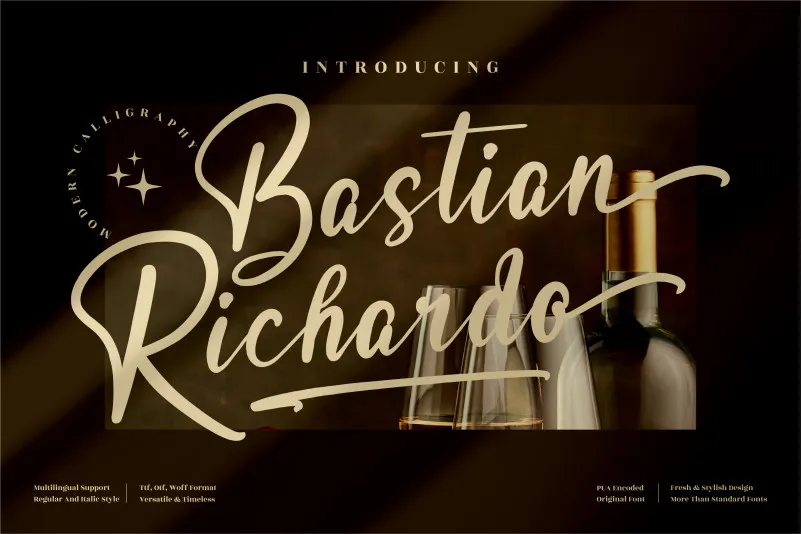
Bastian Richardo Font – Fonte Grátis
Bastian Richardo Font
Esta fonte ‘Bastian Richardo Font’ é uma script relaxada e graciosa, perfeita para projetos de design que buscam um toque sofisticado e elegante. Suas letras dançam ao longo da linha base, criando um charme luxuoso em qualquer criação. Além disso, a sua PUA encoding permite que você facilmente aceda a todas as gírias e swashes, permitindo-lhe explorar o máximo dessa escrita curvilínea e graciosa. Ideal para adicionar um toque de sofisticação aos seus designs, seja em cartões de aniversário, selos de envelope ou qualquer outro projeto que deseje dar um toque a mais.